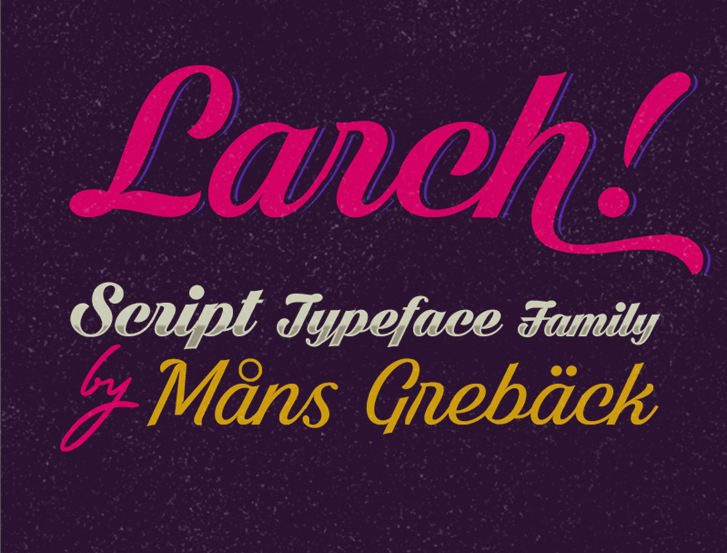
Descubra a beleza do ‘Dark Larch Font’, uma elegante e moderna escolha para projetos tipográficos. Desenvolvida pelo talentoso designer Måns Grebäck, esta fonte script é perfeita para criar texturas suaves e interessantes em design gráfico. A fonte oferece um amplo espectro de opções estilizadas, permitindo que você faça swashes simplesmente adicionando # após uma letra minúscula. Para swashes direcionados à esquerda, basta incluir % seguido por qualquer das letras mencionadas anteriormente: b, d, f, h, i, j, k, l e t. Experimente isso para criar efeitos únicos em seu design. Para obter mais informações ou fazer uma solicitação de licenciamento comercial, visite a página web do designer no site www.mansgreback.com. Nesse local também você encontrará sugestões inspiradoras relacionadas ao mundo das fontes e como usar as ferramentas disponíveis para o seu benefício. Para quem gosta desta fonte ou simplesmente deseja ficar por dentro de novidades relacionadas, acompanhe Måns Grebäck no Facebook através do link http://www.facebook.com/mansgreback. Não deixe de visitar seu site oficial onde você encontrará uma vasta seleção de suas criações excepcionais e inspiradoras.
Designer: Måns Grebäck